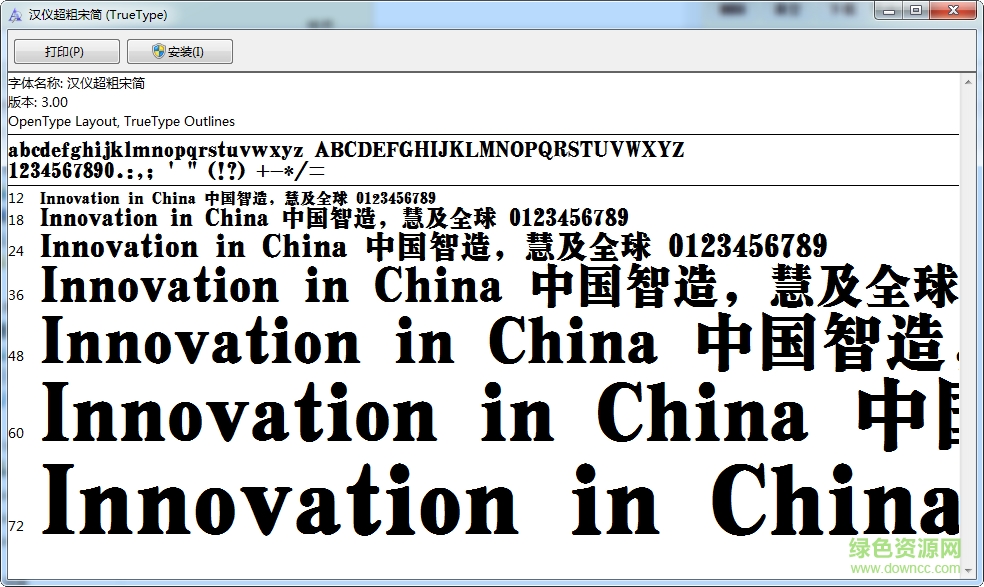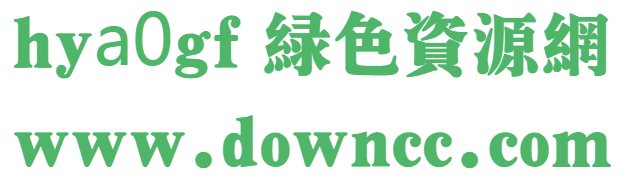
hya0gf字體是一款粗黑碩大的漢儀繁體字體,外形張揚比較吸人眼球,很適合用于美工設(shè)計或產(chǎn)品logo設(shè)計,喜歡的朋友快來下載收藏吧!
該字體端端正正,大大方方,字體比較粗壯,整體效果非常出眾,可以應用于廣告設(shè)計、名片設(shè)計、包裝印刷、產(chǎn)品設(shè)計等方面!